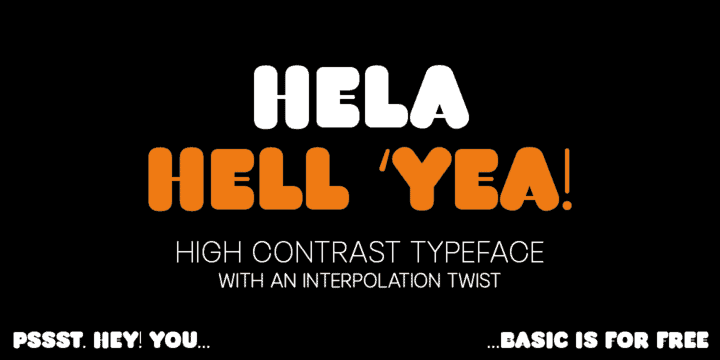
Hela Dysplay Font Family – Fonte Grátis
Hela Dysplay Font Family
A Hela Display Font é uma nova opção no universo das fuentes display para designers inquietos que buscam brilho e originalidade em suas criações. Com seu estilo geometricamente limpo, essa fonte traz um toque divertido de doodle, tornando-a perfeita para aplicar em design de alta impacto e saudações memoráveis. Integrada à letra da antiga empresa czecka de tecidos Helana, que já não existe mais, a Hela apresenta uma característica única: ela não adiciona peso nas estruturas do zero ao preto como muitas outras fuentes fazem. Em vez disso, ela vai adicionando um camada extra de preto às formas leves e esqueléticas da fonte. Esta singularidade torna a Hela uma opção inovadora para designers que procuram algo mais original no meio do pack. Com sua alta contraste, o Hela oferece um arco com twist de interpolação única que proporciona aos designers uma abordagem versátil e desafiadora. A fórmula da Hela não é apenas uma fonte para acomodar em qualquer situação; ela carrega consigo uma história fascinante, conectando-nos à elegância geometricamente simples de uma empresa já defunida, mas que ainda deixa sua marca eterna no ambiente urbano.